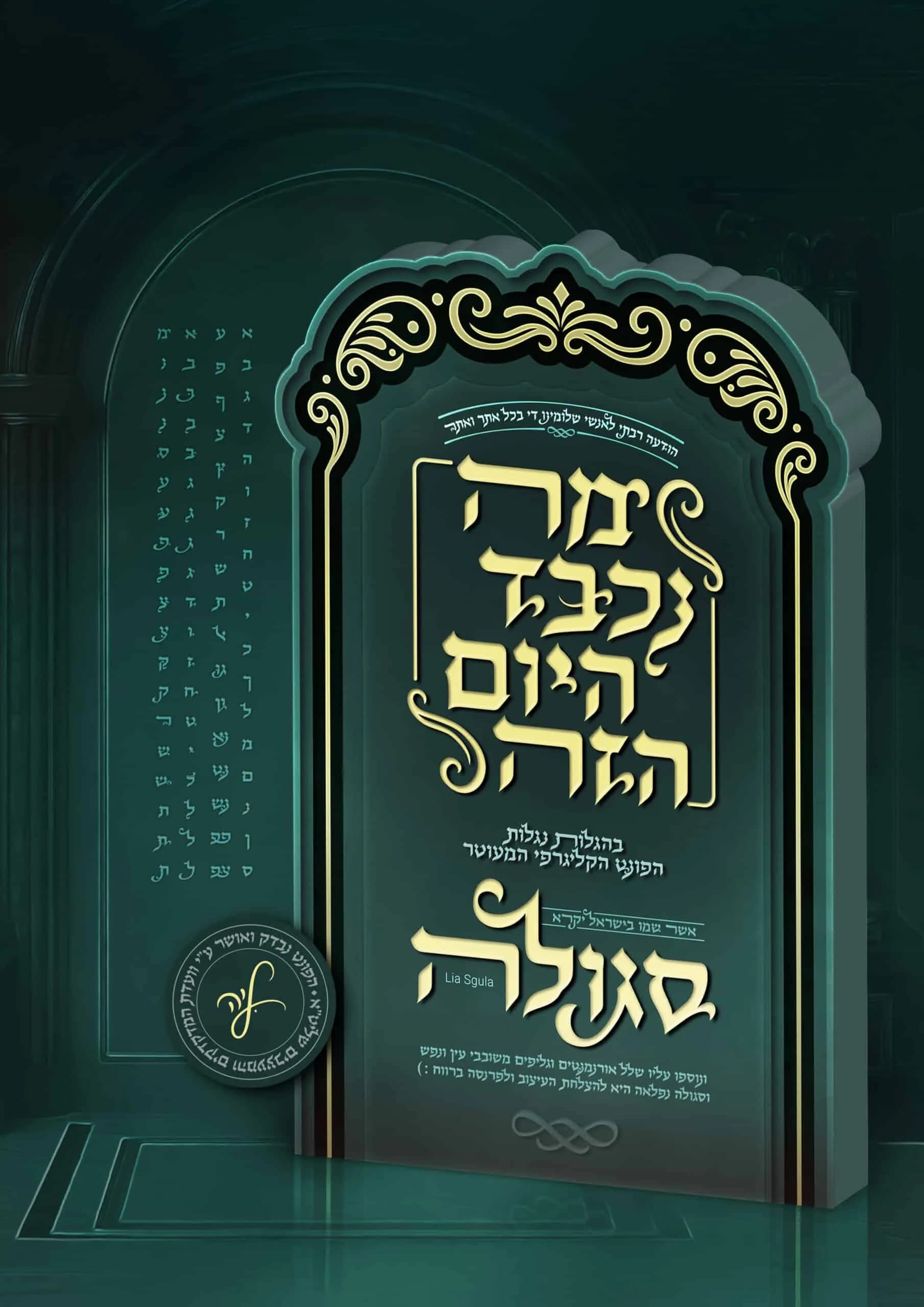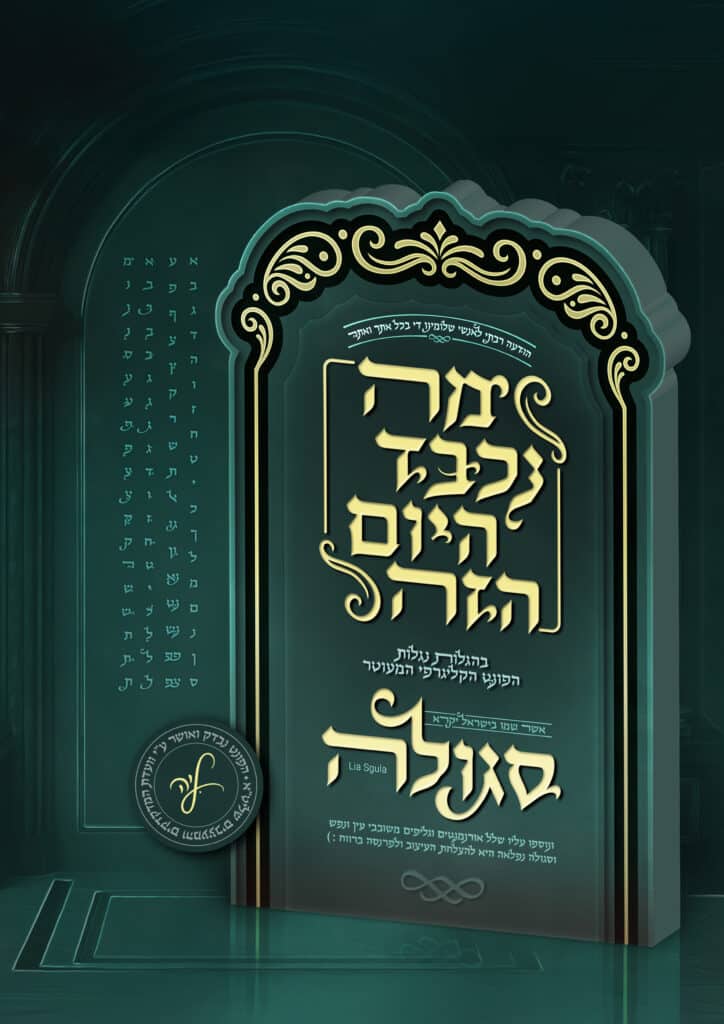
סגולה
פונט סגולה – אותיות של עוצמה ויופי מסורתי "סגולה" הוא פונט דקורטיבי עם אופי אלגנטי ומלא נוכחות, שנבנה בהשראת טיפוגרפיה מסורתית עם טוויסט מודרני. עיצוב האותיות מאופיין בקווים חדים ומדויקים, יחד עם ליגטורות מעוטרות וניקוד מלא, המעניקים לכל מילה תחושת עומק וייחודיות. מאפיינים בולטים: - שילוב בין סגנון עתיק לנגיעה מודרנית, יוצר מראה עוצמתי ויוקרתי. - אותיות עם פרופורציות מחושבות, שמתאימות גם לטקסטים ריצים וגם לכותרות דומיננטיות. - אידיאלי לשימושים רשמיים ומסורתיים כאחד. שימושים מומלצים: - יודאיקה, עיצוב ספרים, מגילות וטקסטים יהודיים. - הזמנות לחתונות, בר מצוות ואירועים מיוחדים. - כותרות מלאות אופי ללוגואים, כרזות ומיתוג עם נוכחות. "סגולה" הוא הבחירה המושלמת לכל מי שמחפש טיפוגרפיה חזקה, מדויקת ומעוררת השראה.
פוֹנְט מְנֻקָּד